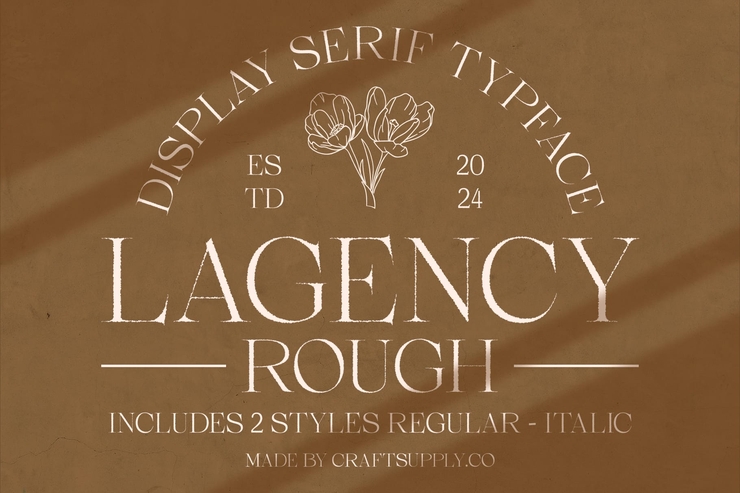
Lagency Raue Elegante Texturierte Stilvolle Englische Schrift
Lagency Rough ist eine einzigartige strukturierte englische Schrift mit eleganten groben Strichen und ausgewogenen Glyphenstrukturen. Ihre unverwechselbare handgezeichnete raue Textur verbindet moderne Mode mit künstlerischem Vintage-Charme und liefert einen hochwertigen und auffälligen visuellen Stil. Diese stilvolle Schrift eignet sich perfekt für Markenlogos, Modeposter, Web-Schlagzeilen, E-Commerce-Banner, Produktverpackungen, Social-Media-Grafiken und dekorative Typografie. Komplett mit Groß- und Kleinbuchstaben ist sie hochgradig skalierbar und lässt sich leicht an Farben, Größen und Layouts anpassen, wobei die ursprüngliche raue Textur erhalten bleibt. Geeignet für Grafikdesigner, Kreativstudios und kommerzielle Branding-Projekte, um allen Designs einen exklusiven künstlerischen Charakter zu verleihen works.Free kommerzielle Nutzung / Kein Copyright 1